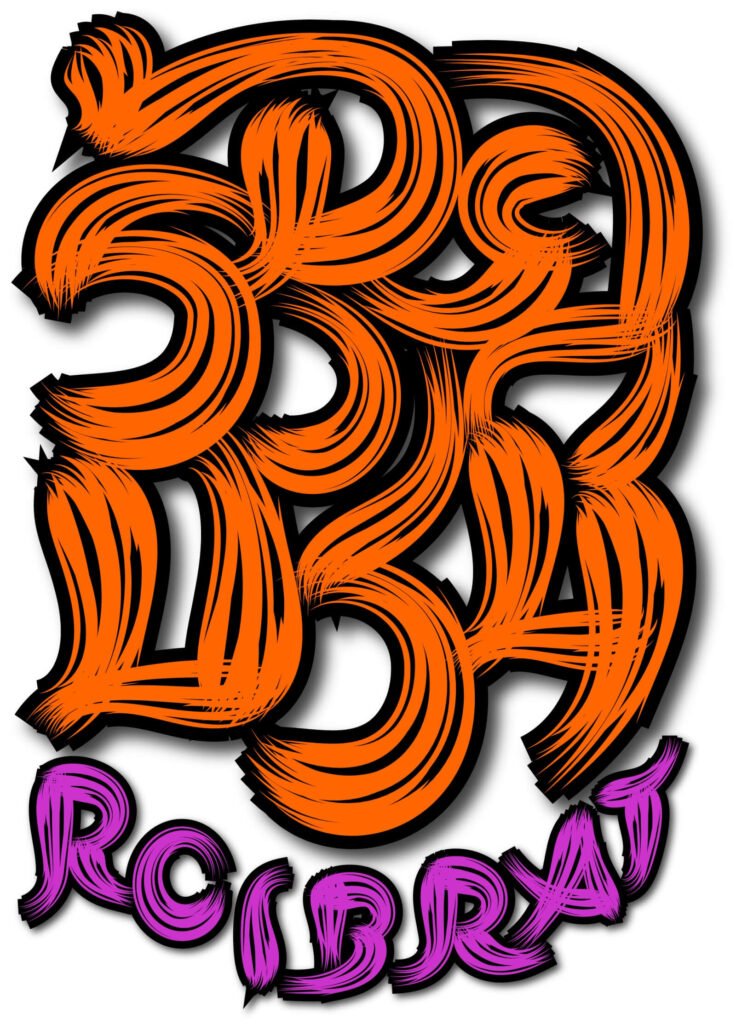
ร้อยบรัช (SP_RoiBrat)
ย้อนกลิ่นอายในวันวาน กับหนังจีนกำลังภายใน แอ็กชันมันส์ทะลักจุดเดือด จนเกิดเป็นฟอนต์ร้อยบรัช สะบัดลาย
ส่ายลีลา โยกท่วงท่า พริ้วไหวเอน